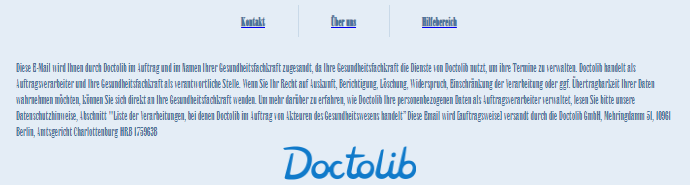
die Forumssuche hat mir erstmal nicht die gewünschten Ergebnisse geliefert, da bei mir zwar eine Schrift angezeigt wird, aber diese ziemlich unleserlich ist:
Das ist die Signatur von doctolib. Manche e-Mails von mir werden in genau dieser Schriftart angezeigt.
Manchmal lade ich Webseiten, wo ich für einen ganz kurzen Moment genau dieser Schriftart beim Laden sehe, bis sie dann schnell "übersetzt" wird in eine andere, möglicherweise Chrome-interne Schriftart. Andere Webseiten widerrum werden ebenfalls in genau dieser Schriftart angezeigt.
Ich wüsste jetzt auch nicht, was ich in der Systemsteuerung bei Schriftarten einstellen sollte. Es ist ja völlig in Ordnung, wenn andere Leute ihre eigene Schriftart im Emailverkehr verwenden, aber dann doch bitte eine leserliche und nicht eine solch gequetschte Schriftart.
Im Firefox ist die Schriftart bei Mails mit der unleserlichen Schriftart jedoch anders, also leserlich.